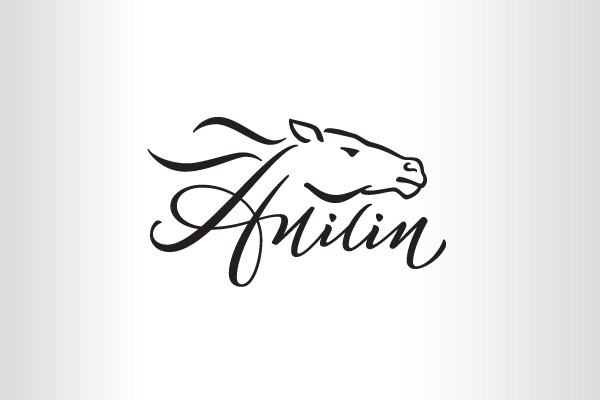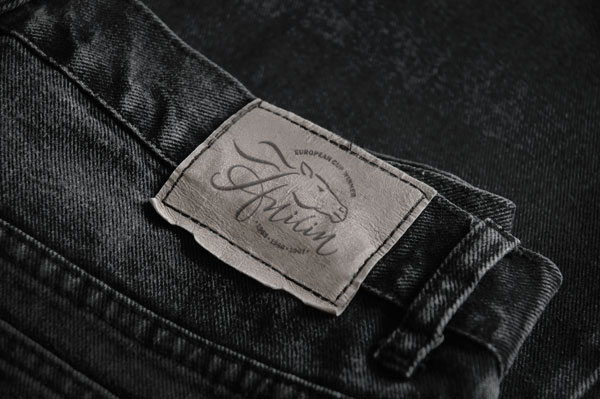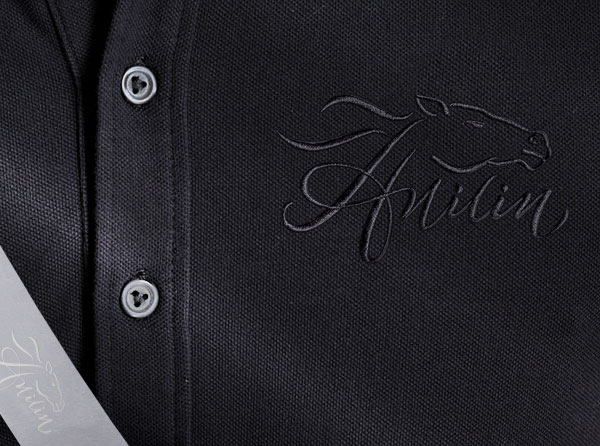
Анилин
Логотип для производителя одежды повседневного стиля. Пожеланием заказчика было присутствие лошади в логотипе, Анилина, скакуна-победителя международных соревнований 60-х годов. Каллиграфическая надпись объединена со знаком.